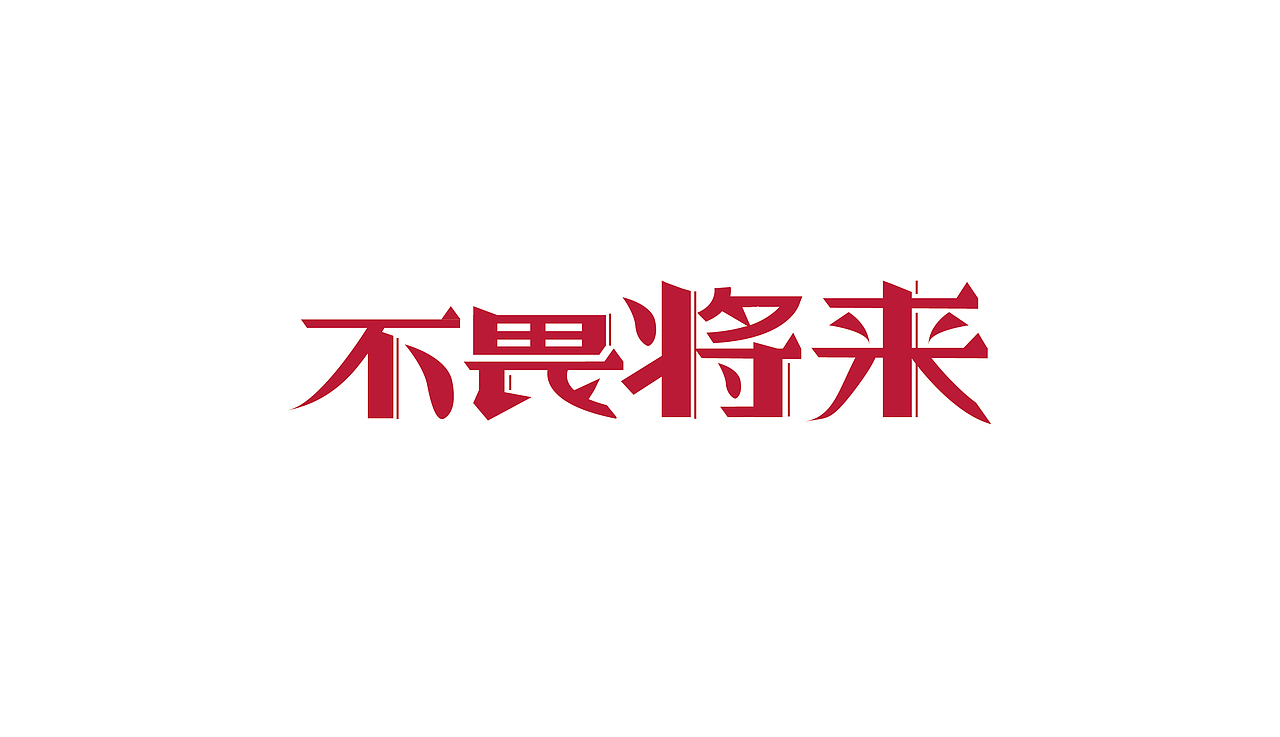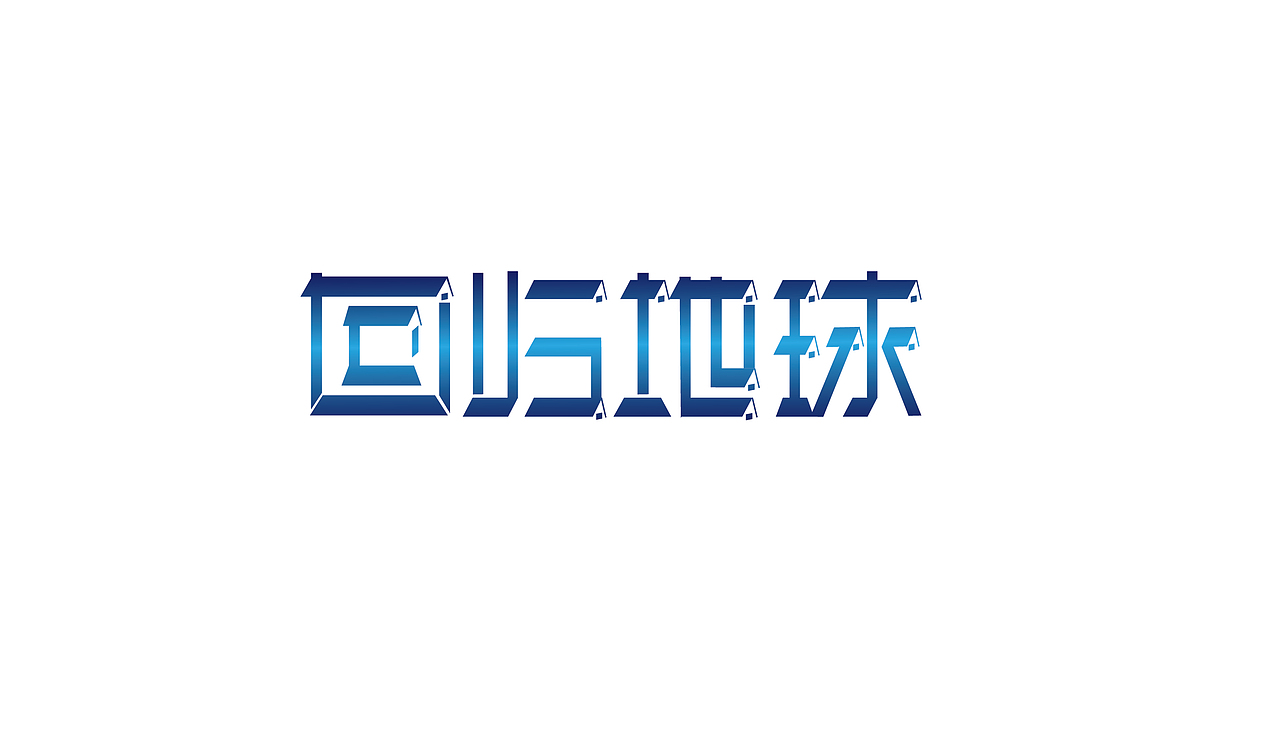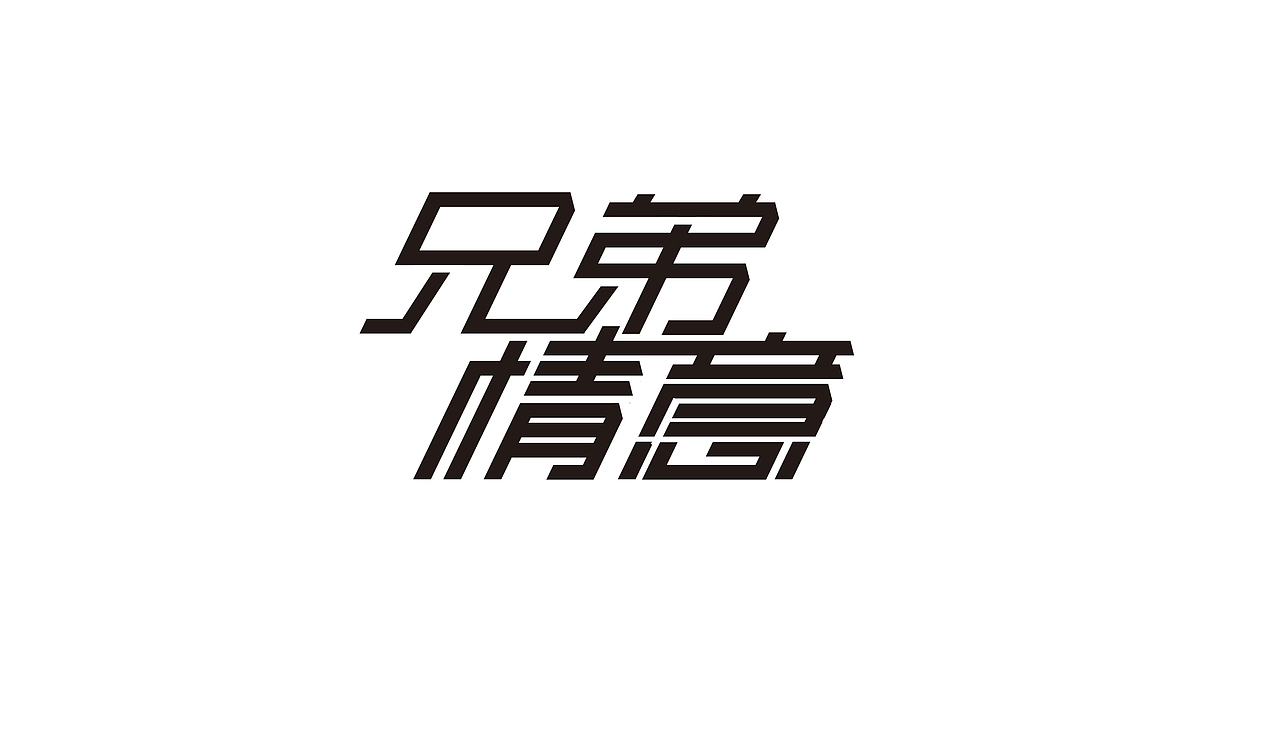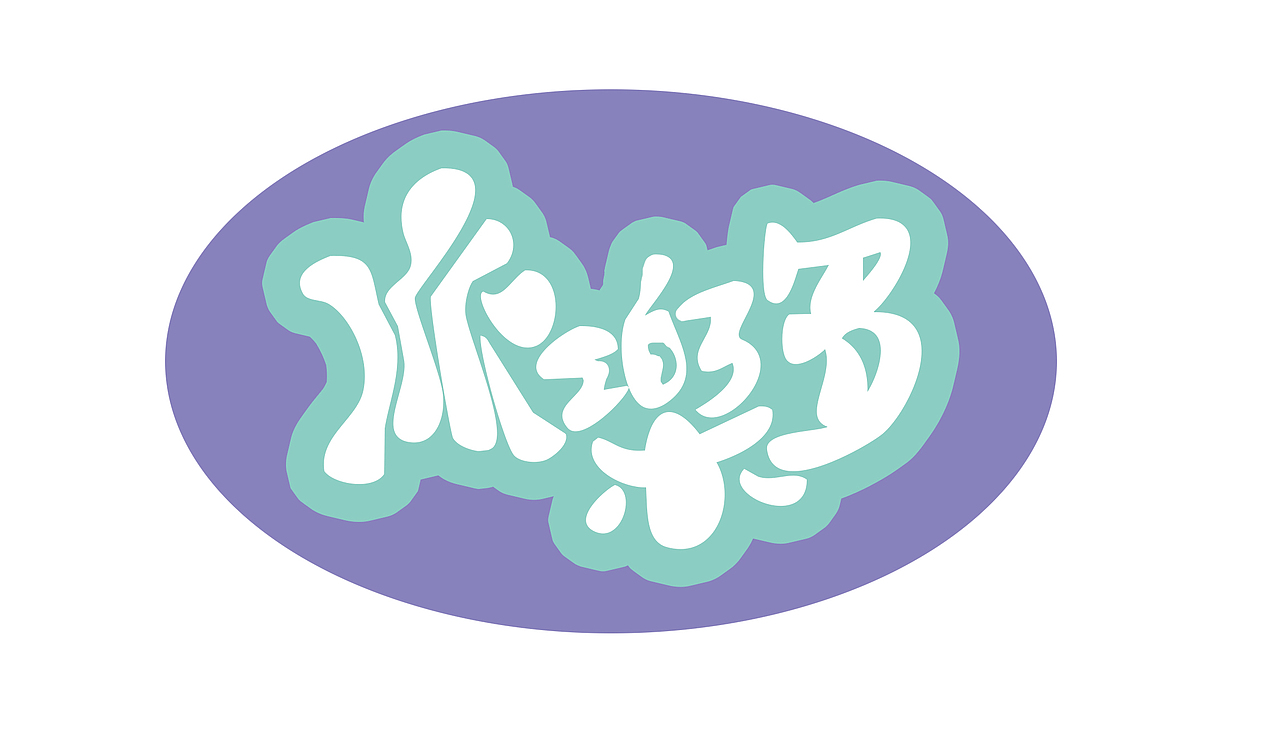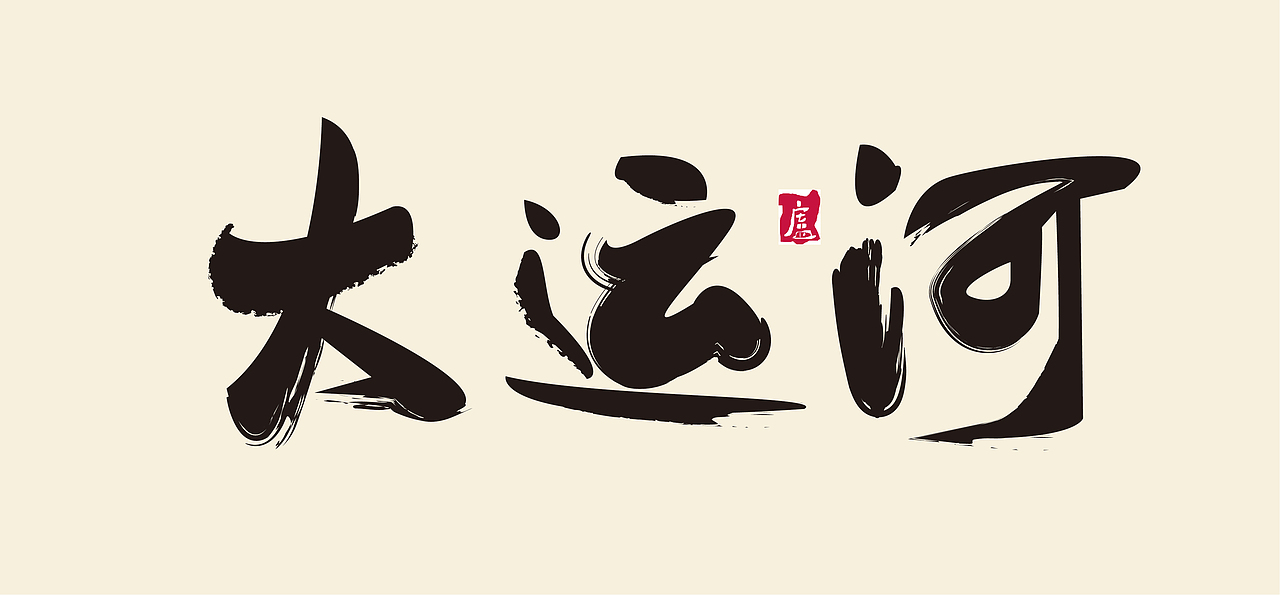
这两天做的几种字体 一次次的积累方法 字体的重要性对于设计来说我认为那是相当地重要啊。
细线圆体来增加时尚感简约风
加个边框就可以成为化妆品或日用品的logo
对于宋体进行的改造。不畏将来——
换个颜色 我们不一样——每个字体都有不同的方向。
兄弟情"意“
卡通风 派乐多
书法字体 大大大运河
文文文化天博